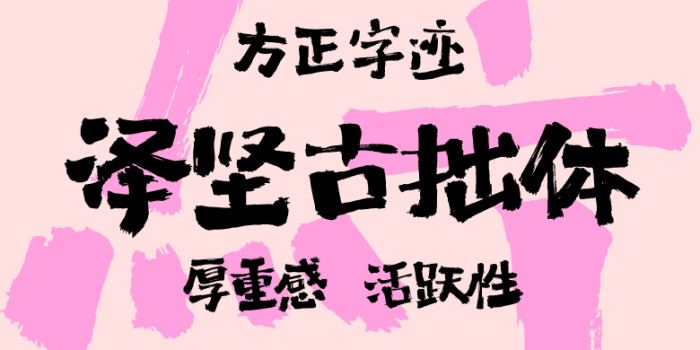
方正字迹-泽坚古拙体
方正字迹-柏榆手书由方正字库张泽坚设计师出品的艺术字体,字体比较古朴和拙,拙中带巧,字中有适当的飞白,适合应用于艺术设计、平面宣传设计、网页设计,书法等领域。
这款字整体就是比较古朴和拙,拙中带巧,字中有适当的飞白,使这个字具有厚重感的同时带有一定的活跃性,适用于文创品牌包装、餐饮广告、门店招牌、餐饮室内装饰、影视剧海报、游戏海报等。